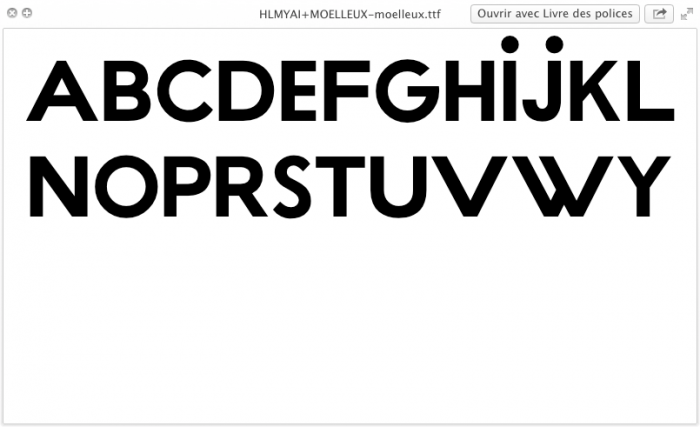
Kennt jemand diesen Entwurf?
Genau. Aus diesem PDF habe ich die extrahiert. Aber seit 2010 hat sich da anscheinend nichts Neues ergeben, wie mir scheint. Denn die Gotham bzw. Bahnhofs-Futura ist's ja nicht ..
Das ist schon ein eigenständiger Entwurf. Ob der eventuell unter einem anderen Namen veröffentlicht wurde, weiß ich aber nicht.
Na dann mal m bisserl Geduld, das ding ist ja wirklich viel zu unkompliziert (und auch ein biswserl Gurkig, den E und F pasen irgendwie nicht so ganz zusammen... Mal sehen, wie sich das so zusammenklatscht W X und Z muss man sich dann eben erraten, wie auch Satzzeichen und Zifferen, wenns dann mus :-)
Vielleicht ist das ja auch Absicht mit dem E und dem F. Das sind Studenten an der ENSAD (steht zumindest in dem Bild auf http://www.typografie.info/3/topic/22847-suche-diese-grotesk/), das ist die École nationale supérieure des Arts Décoratifs de Paris. "Supérieure", Achtung! Also ..
Bei der Gotham haben sie schon viel abgekuckt, oder?
Da hat einer Spaß, was?
Aber das M ist schon hardcore, oder?
Allerdings: Wenn ich die Schrift bei mir installiere funktionieren die Ziffern nicht. Kann das sein?
ist ja auch der erste abguss, zahlen sind noch nicht gezeichnet.
Und ja, M ist hardcore, wie ja auch W. Ich hab das soi gewählt, weil auch so manches anderes in der Schrift wohl bewust etwas "schief" ist, wie die dicken I und J Punkte, das vergleichsweise zu schmale E und S, welches in der Originalgrafig auch noch fürchterlich eierig war. Ich habe versucht, dies zuzmindest etwas von den Beulen zu befreien. Jetzt hab ich erst mal die wichtigsten Satzzeichen gezimmert. Auch, da ja so ne Art Versalschrift, auch ein ẞ
Mal sehn, die Ziffern dürfen ja dann auch nicht so Übervernünfig sein. Die Gotham-3 past aber schon recht gut.
Noch immer ohne Ziffern, dafür Buchstaben komplett (auch Akzente und ẞ) und die meisten Satzzeichen.
Ist schön geworden.
So kleine Details wie der Schrägschnitt in der 2 und der 4 .. die abgeschnittene 7 ..
Und die 3 hat so ein dickes Dach auf dem Kopf ..
Auch wenn aller guten Dinge 3 sind, hier der 4. Teil:
Hinzugekommen die Ost-Europa-Lateinbuchstaben (also auch für meine "Nachbarn" hier oben, sowie noch einiges an Zurichtung:
Watauchimma (also: watt auch imma = was auch immer) ist allerdings erst mal ein Arbeitsname. Mir fehlt noch ein schöner richtiger Name sofern ich Wattauchimma nicht doch lasen soll :-)
Na, “moelleux”, heißt markhaltig, weich, flaumig, mollig.
Ist da eventuell was dabei?
Mountain Sans, Mont Sans, Mount Sans, Alpen Sans, Panorama Sans – irgendein Name, der auf das Berge-M Bezug nimmt, vielleicht?
Oder irgendein Berg mit so 'ner Doppelspitze. Sind keine Bergler unter uns?
Doppelspitze
Lieber ’ne echte: Lukasmiro oder – wenn du gleich gleich noch die Sprachunterstützung illustrieren willst – Łukaszmiro?
O Gott, da gibt's so viele .. Und weil ich überhaupt nicht gerne auf Bergen rumklettere, kenn ich mich da überhaupt nicht aus.
Der Uschba gefällt mir aber, klingt auch gut.
Beim Elbrus denk ich sofort an die Wehrmacht ..
@catfonts: Hast Du nicht ein Kürzel, das Du voranstellen könntest? CF Uschba oder so?
Normalerweise schrillen hier doch immer die Alarmglocken, wenn Schriften als potenzielle Plagiate gehandelt werden. Daher wundert es mich schon, dass in diesem Fall anscheinend niemand ein Problem damit hat. Ich möchte diesbezüglich auch gar kein großes Fass aufmachen, aber ein wenig irritiert bin ich schon, dass hier ein originärer Entwurf nachgebaut und frei zugänglich gemacht wird. Oder wie seht ihr das?